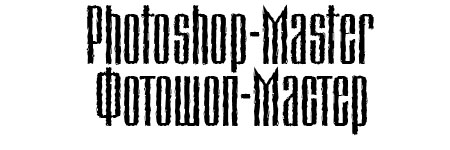
Дополнения Шрифты Татьяна Гапонова 19 ноября 2008 Шрифт - MatterhornCTT Декоративный шрифт с поддержкой русского языка. Скачать Шрифт - MatterhornCTT
Смущает только межбуквенный интервал, а так всё отлично и бархатно)
Есть ещё второй шрифт из СТАЛКЕРА,как в надписи Сталкер на коробке игры
хороший шрифт) уже запилено на ФШ) только нужен еще один который в игре применяется
это шрифт названия книг